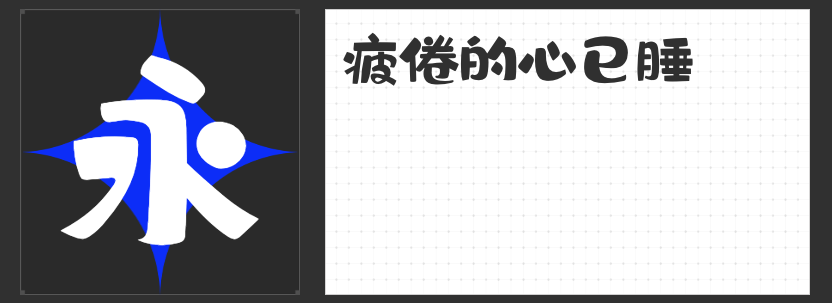
引爆视觉转化力!电商设计师必备的4款高转化字体
在注意力经济主导的电商战场,字体不仅是信息载体,更是刺激用户决策的视觉武器。以下四款字体以独特的性格张力,精准匹配促销氛围、品牌调性、活动场景三大核心需求,助力点击率与转化率双提升。
一、字恋狂漫野 鸣风
这款字体以「手写体骨架+几何化改良」破解电商设计悖论:既保留手写温度,又具备数字屏显的清晰骨架。去钩处理的弯折笔画形成通透视觉流,错落字重节奏打破呆板陈列,尤其适合「限时特惠」「满减攻略」等需要引导视线路径的长文案排版。灰度均匀的直线组合,在商品详情页中确保阅读舒适度的同时,赋予促销信息手写告示牌的信任感。
二、字恋狂嗨玩简
当Z世代主导消费决策,这款「笨拙可爱体」精准狙击年轻群体。方正字形如乐高积木般充满搭建趣味,重心下沉设计天然适配「立即抢购」「拼团砍价」等行动号召按钮。在直播预告海报、社群裂变图中,其憨态可掬的视觉性格能快速建立品牌亲和力,配合动态表情包使用时,更能激发用户社交分享欲。
三、励字憨憨简
圆润饱满的弧形笔画自带萌系基因,天然适配母婴用品、零食坚果、宠物用品等「可爱经济」赛道。其装饰性极强的字形设计,在品牌LOGO、商品主图中可独立成为视觉符号,配合IP形象使用时能强化品牌记忆点。在「618」「双11」大促期间,用此字体设计的活动主题,能快速传递欢乐购物氛围。
四、励字励黑简
这款无衬线超粗字体堪称电商视觉的「强力胶」,方正饱满的字面结构在首焦海报、导航栏、价格标签等场景中形成视觉重力区。去除字肩的极简设计,使「限时5折」「镇店之宝」等关键信息在信息洪流中脱颖而出,特别适合需要瞬间抓睛的促销场景。其朴素大方的气质,亦能平衡复杂背景中的视觉噪音。
电商设计的本质是0.1秒的视觉战争。这四款字体分别从「情绪温度」「社交货币」「品牌人格」「信息聚焦」四个维度构建视觉转化闭环。当字体战略与运营策略同频共振时,每一像素都在为GMV增长助力。